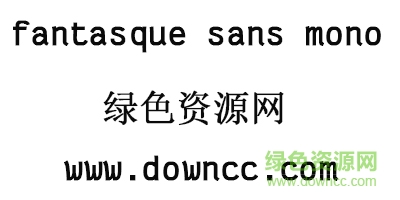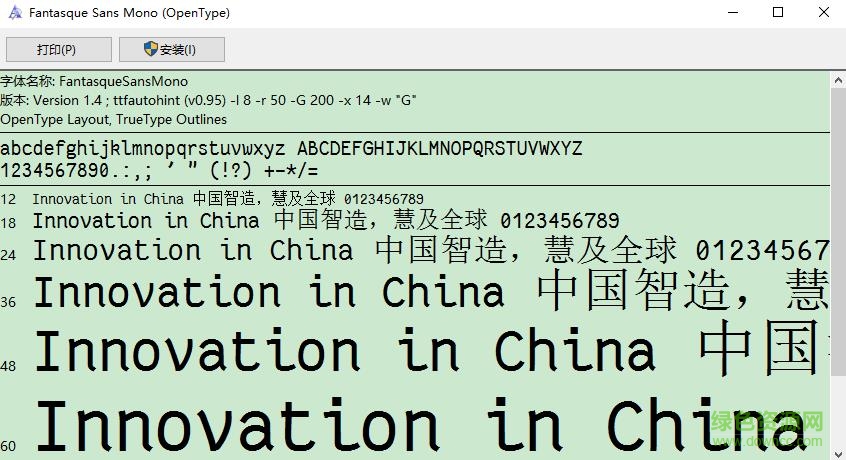
fantasque sans mono是一款非常實(shí)用的電腦英文字體,這款字體字形生動(dòng),整體效果非常出色,應(yīng)用范圍也十分廣泛,感興趣的朋友可以來綠色資源網(wǎng)下載體驗(yàn)!
長(zhǎng)體字有上下流動(dòng)的感覺,
扁體字有左右流動(dòng)的動(dòng)感,
斜字有向前或向斜流動(dòng)的動(dòng)感。